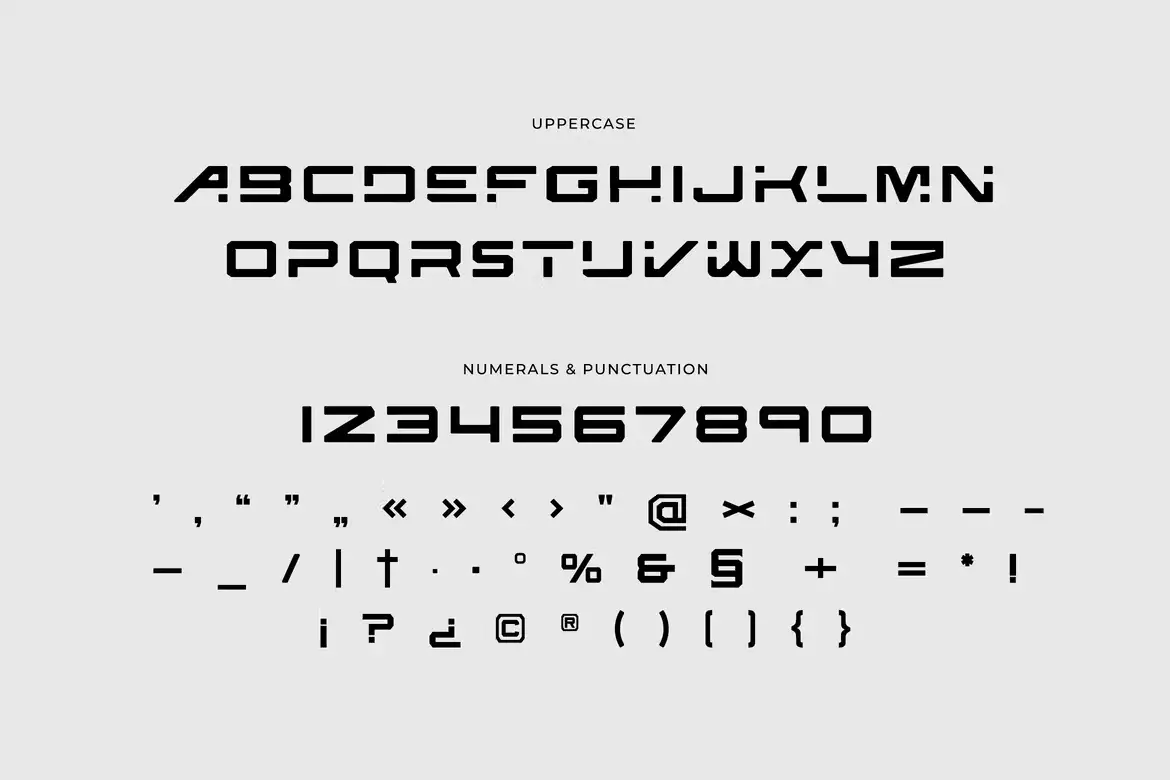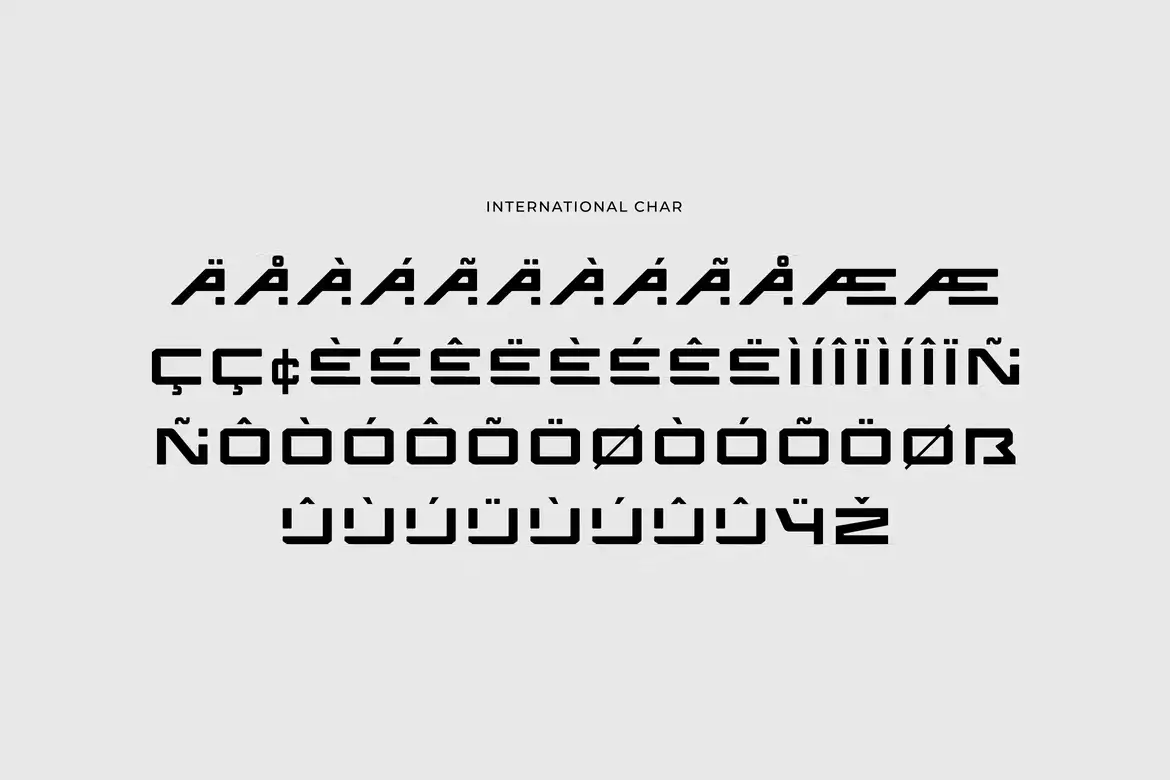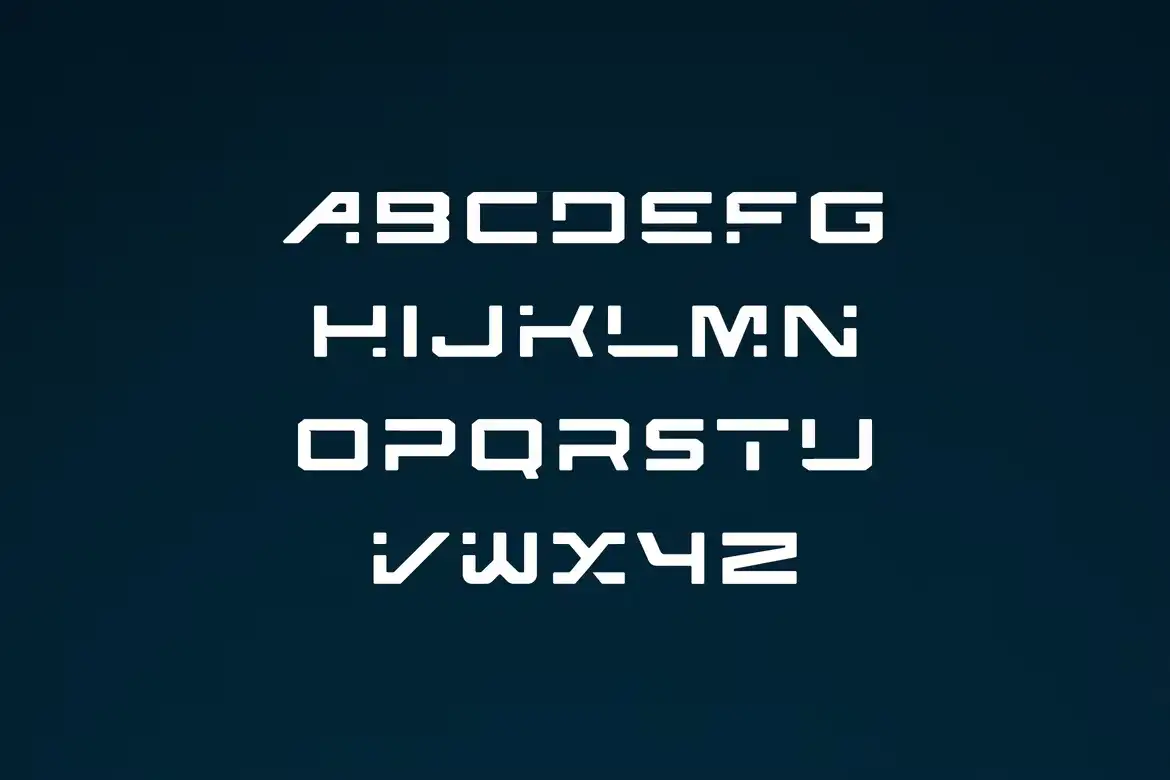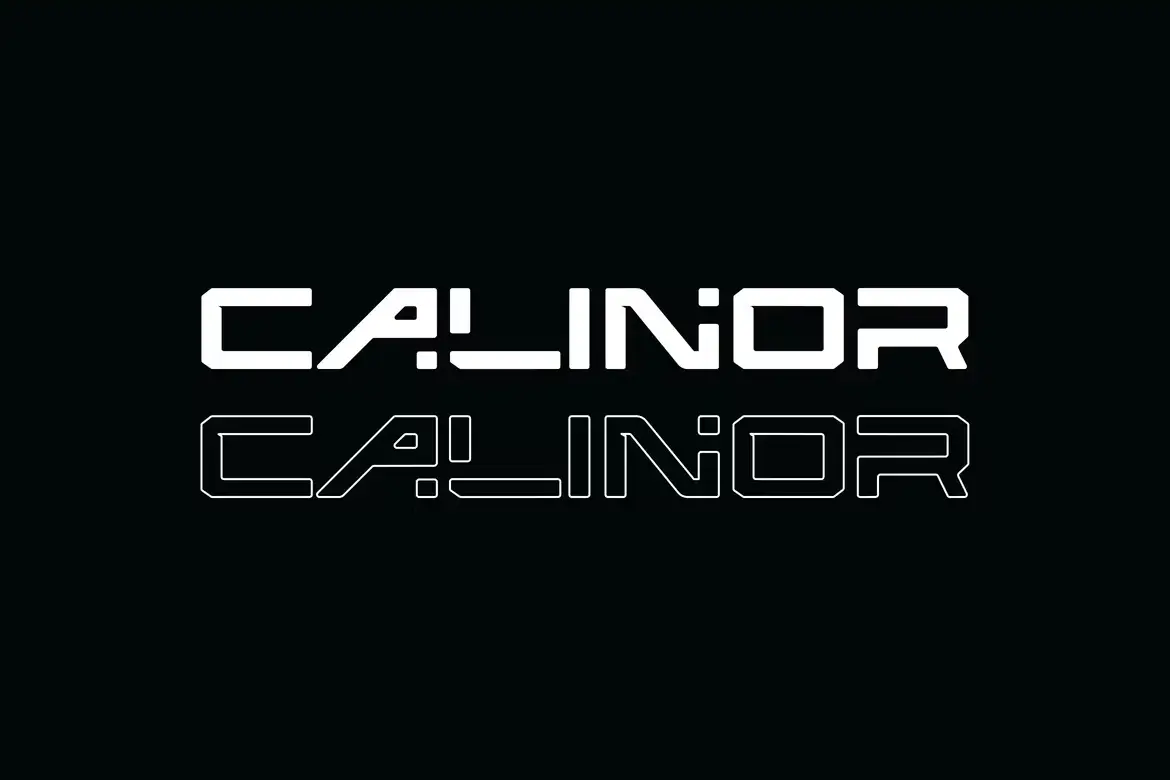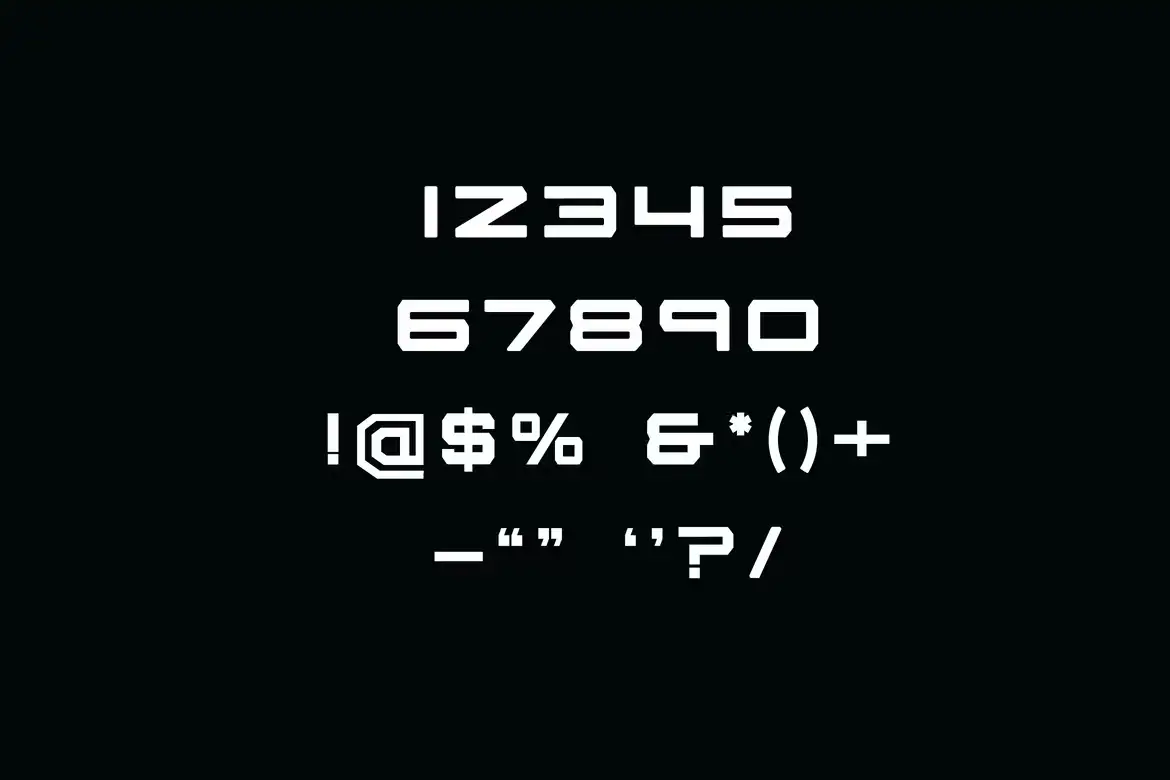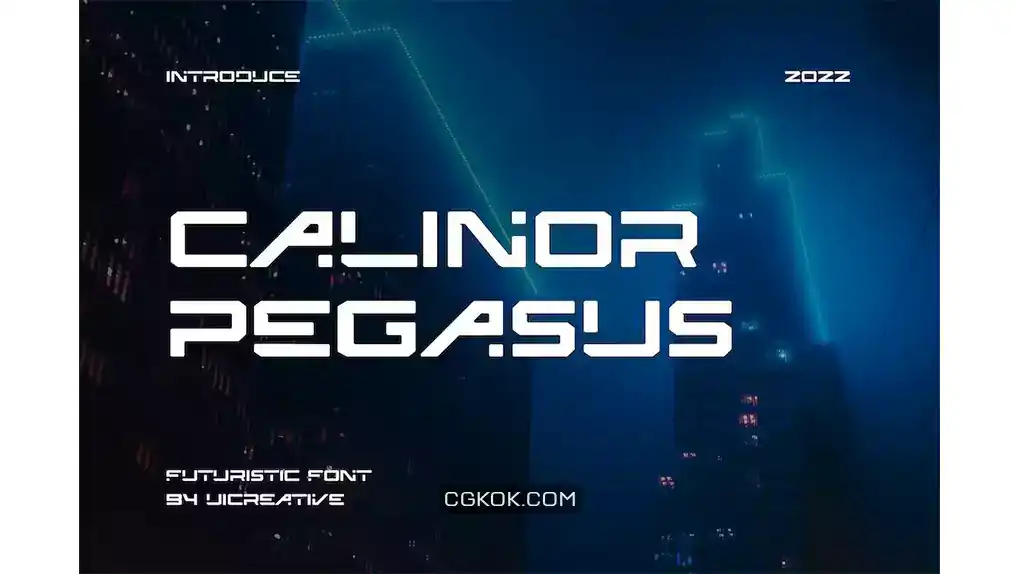
دانلود فونت سنس سریف علمی تخیلی مدرن Calinor Pegasus Futuristic Sans Serif Font : این مجموعه شامل یک فونت فانتزی است که برای امضا، برندینگ، لوگو، کارت، عروسی، نقل قول های تایپوگرافی، کاور مجله یا کتاب، سربرگ وبسایت، لباس، طراحی بسته بندی و غیره مناسب میباشد.
- عنوان مجموعه: Calinor Pegasus Futuristic Sans Serif Font
- سبک: Sans-Serif
- فضا بین حروف: معمولی
- اندازه بهینه: تمامی سایز ها